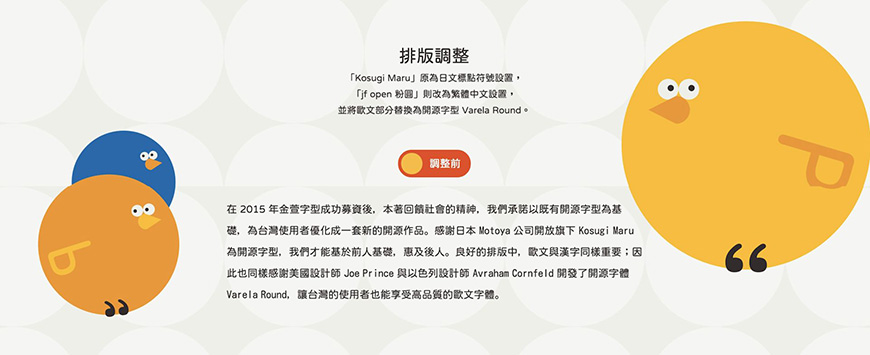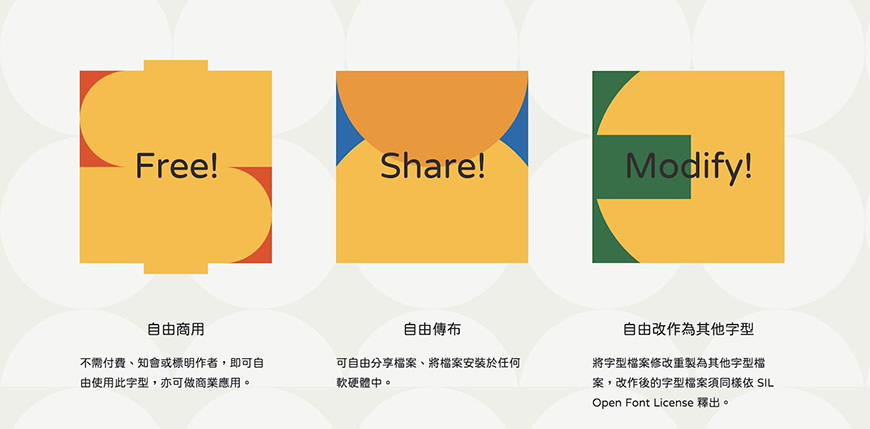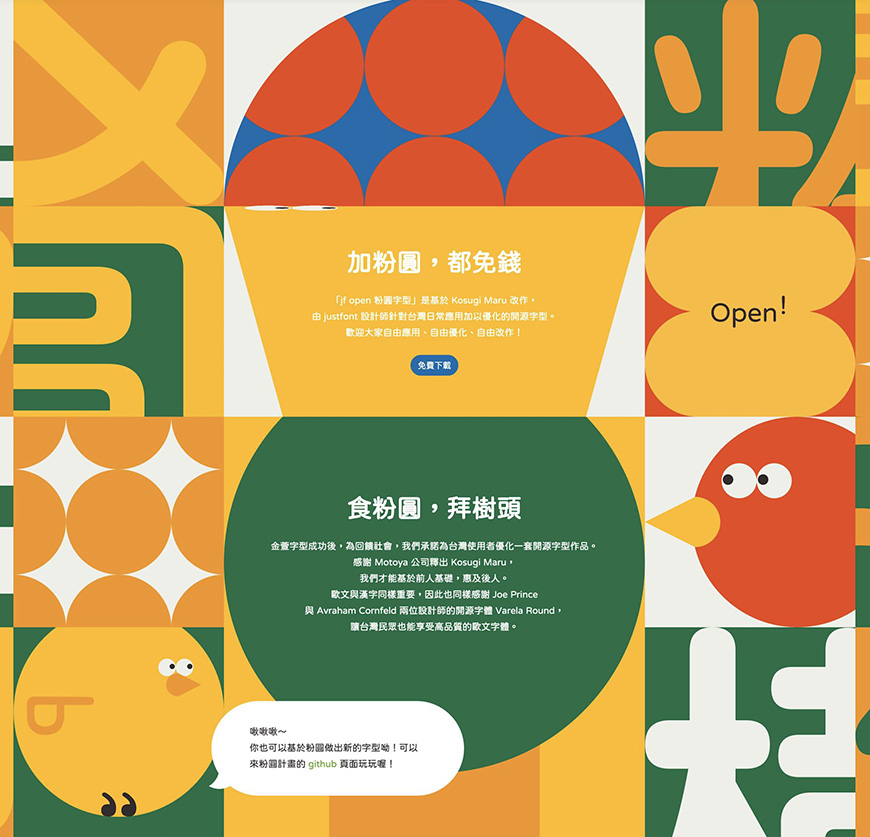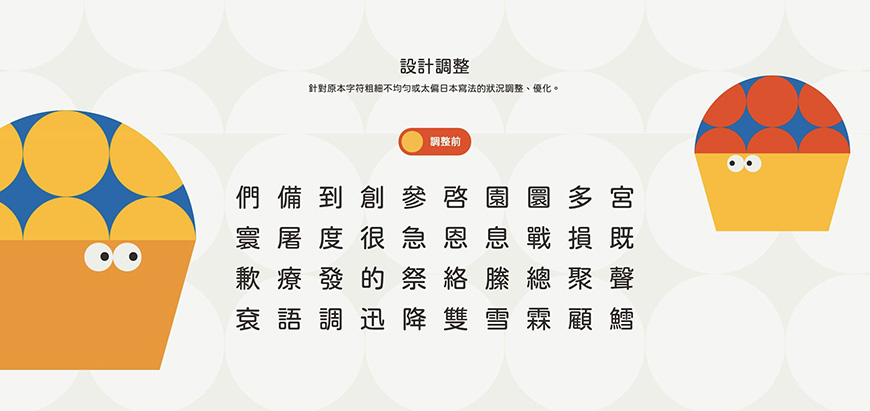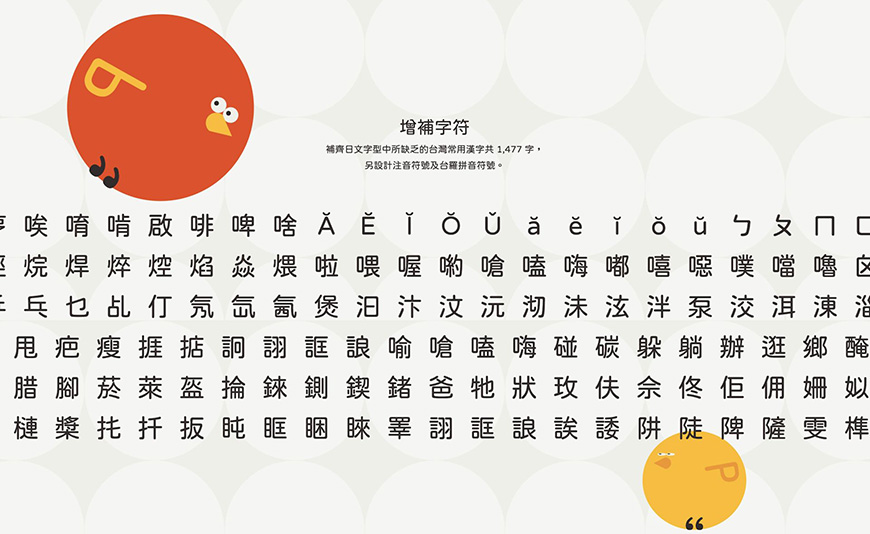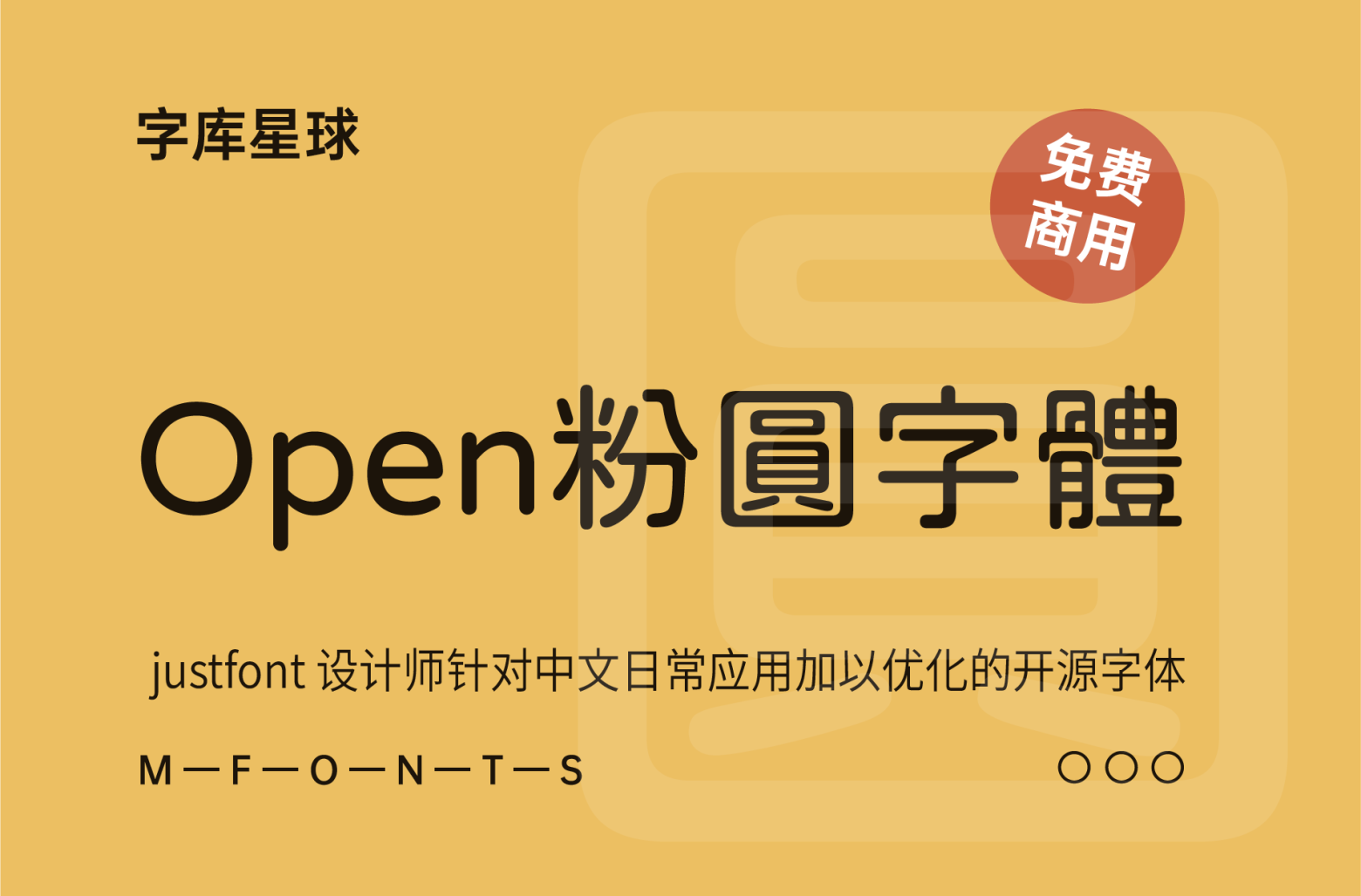
jf open 粉圆
jf open 粉圆字体中汉字基于 Kosugi Maru(小杉圆体),英文基于 Verala Round,由 justfont 设计师针对中文日常应用加以优化的开源字型。
jf open 粉圆在小杉圆体原日文字体的基础上,额外设计了 1,477 个中国台湾地区的常用字、注音符号以及汉语拼音,并修订排版设定,以适应汉字的使用需求。更改进了灰度质量,让你的排版更美丽!
open 粉圆体针对小杉圆体原日文字体的字符粗细不均匀或太偏日本写法的状况进行调整、优化,以适应中文汉字的使用需求。
在排版的调整上,小杉圆体原为日文字型标点符号设计,jf open 粉圆则将其改为繁体中文标点符号设置。